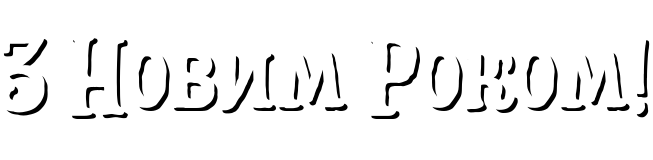
Сімейство: Hatter Display Pro (12 шрифтів)
Асоціації зі шрифтом Hatter Display Pro ShadowОсобистість і характер шрифта:
колючий, ролевий, кущистий, рослинний, лісовий, складний, химерний, готичний, закручений, кріповий, старомодний, тісний, оригінальний, характерний, грайливий, самобутній, кучерявий, артистичний, танцюючий, цікавий, декоративний, динамічний, колоритний, живий, крафтовий, чарівний, неформальний, непосидючий, неслухняний, пустотливий, рухливий, задерикуватий, рукотворний, натуральний, вигадливий, домашній, органічний, казковий, старовинний, ламповий, ремісничий, фермерський, творчий, чаклунський, магічний, святковий, веселий, смішний, жартівливий, стрибучий, хуліганський, наївний, епатажний, мультяшний, дотепний, осінній, зловісний, злий, цвинтарний, страшний, мертвий, фрік, пекельний, дивний, божевільний, окультний, таємничий, загадковий, експериментальний, моторошний, гарбузовий, повзучий, гнучкий, гарячий, вогняний, артізанальний, екзотичний, вернакулярний, макабричний
тату, сувенір, Чарівна казка, меню, карти, сувій, король, королева, дракон, фентезі, кузня, ремесло, антикваріат, пиво, таверна, свято, сад, цукерки, гра, театр, осінь, страшилка, пугало, гарбуз, дитяча книжка, пригоди, анімація, солодощі, казка, ферма, татуювання, геловін, гумор, табір, закуска, чарівник, чаклун, спеції, хенд мейд, тварини, тварюки, прикраса, хоррор, фільм жахів, іграшка, розваги, атракціон, вірус, хвороба, кладовище, закляття, магія, прокляття, мультфільм, мрець, привид, жуки, павуки, комахи, монстр, чудовисько, відьма, зомбі, Самайн, чіпси, квест, графіка, ілюстрація, дім, декор Шрифт має ознаки стилів: